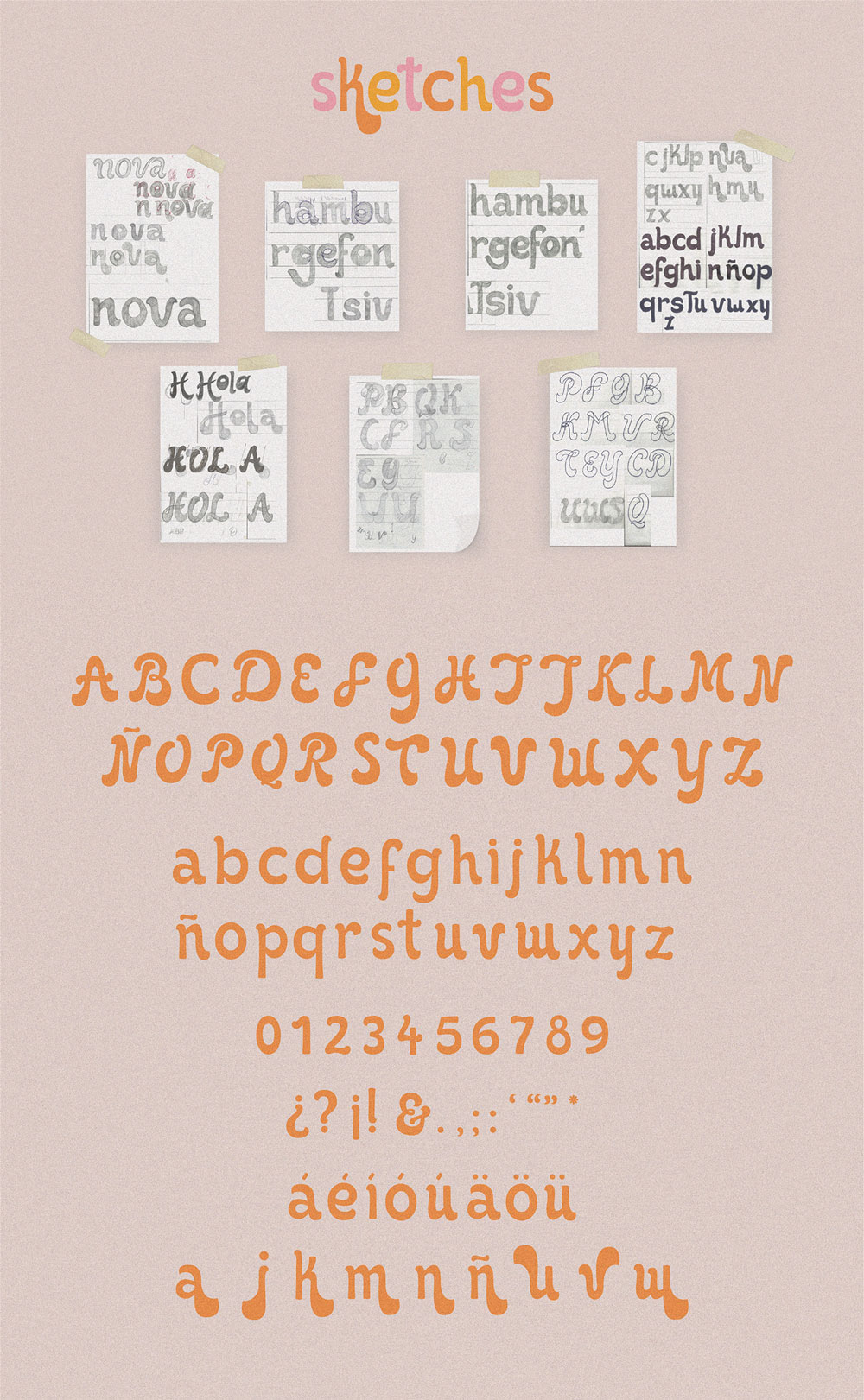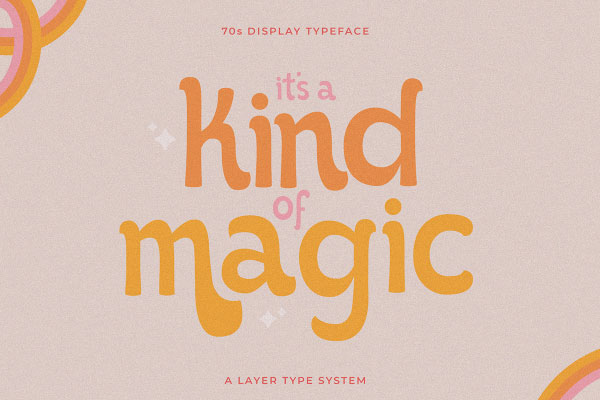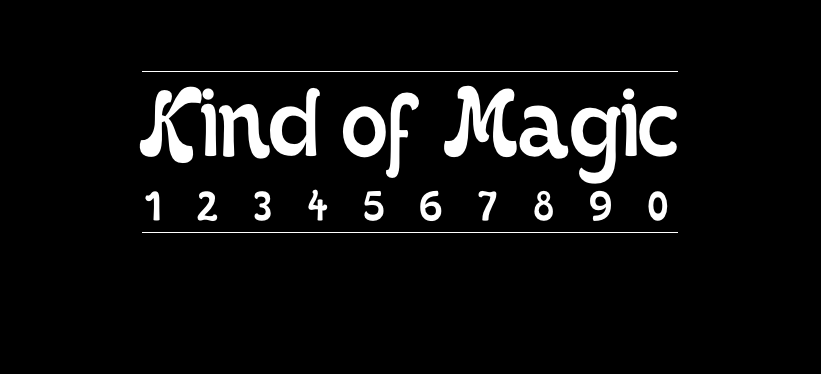
Kind of Magic
Kind of Magic的作者是来自阿根廷的Lucia Zanotti,该字体家族的概念是70年代复古,充满了不同形状,纹理和颜色的特征。使用柔和的色调,如浅粉色,绿色或蓝色被使用和点缀着红色、黄色、紫红色等颜色,这是一种具有个性的风格,在当前环境下是可识别的。当时的排印都是徒手制作的,所以这次重新解释尝试模拟这些笔触,给过去和将来的事物以现代的触感。
Kind of Magic字形笨拙可爱,充满童趣,可用于儿童、幼稚等需要亲和力的场合。